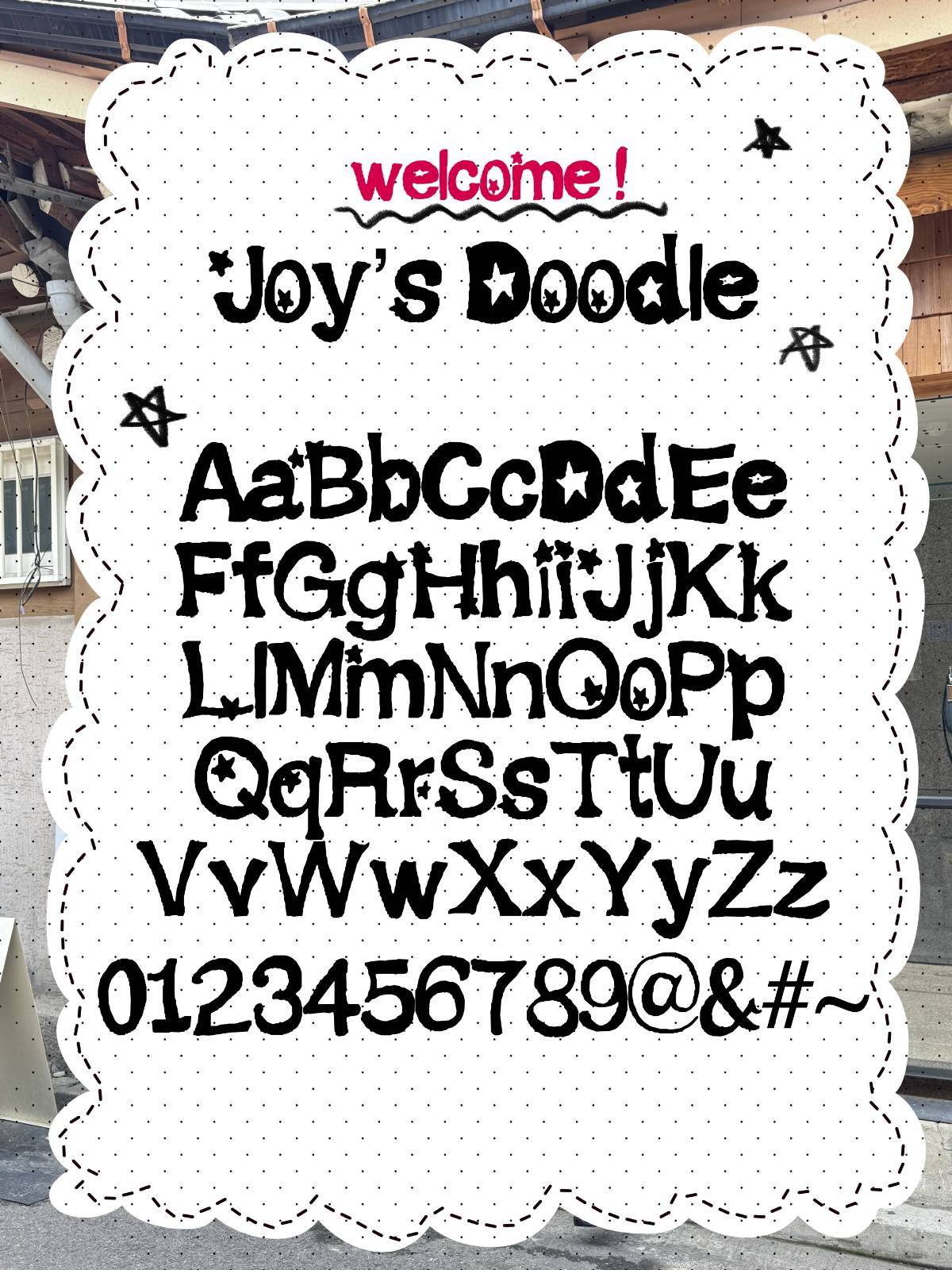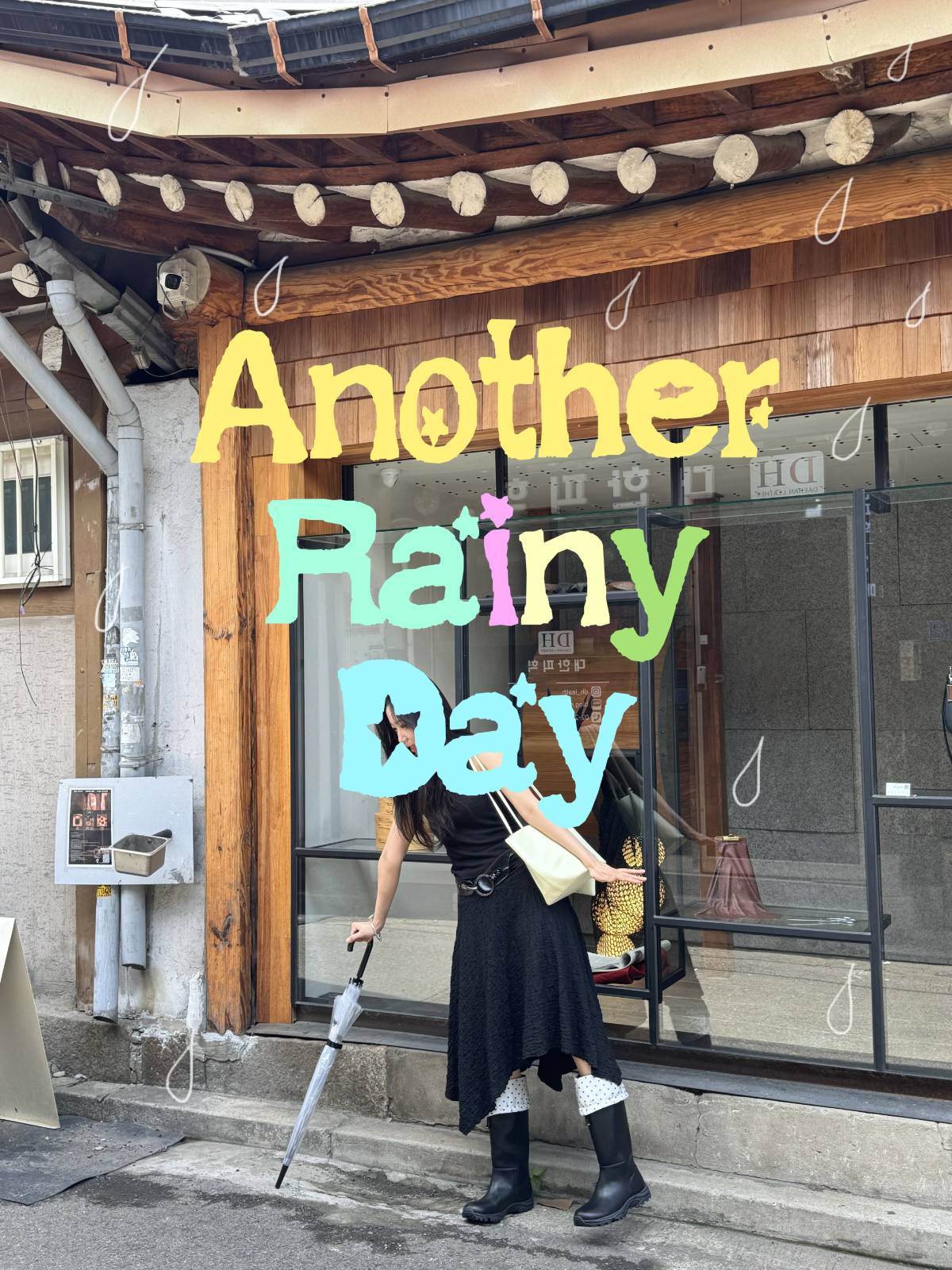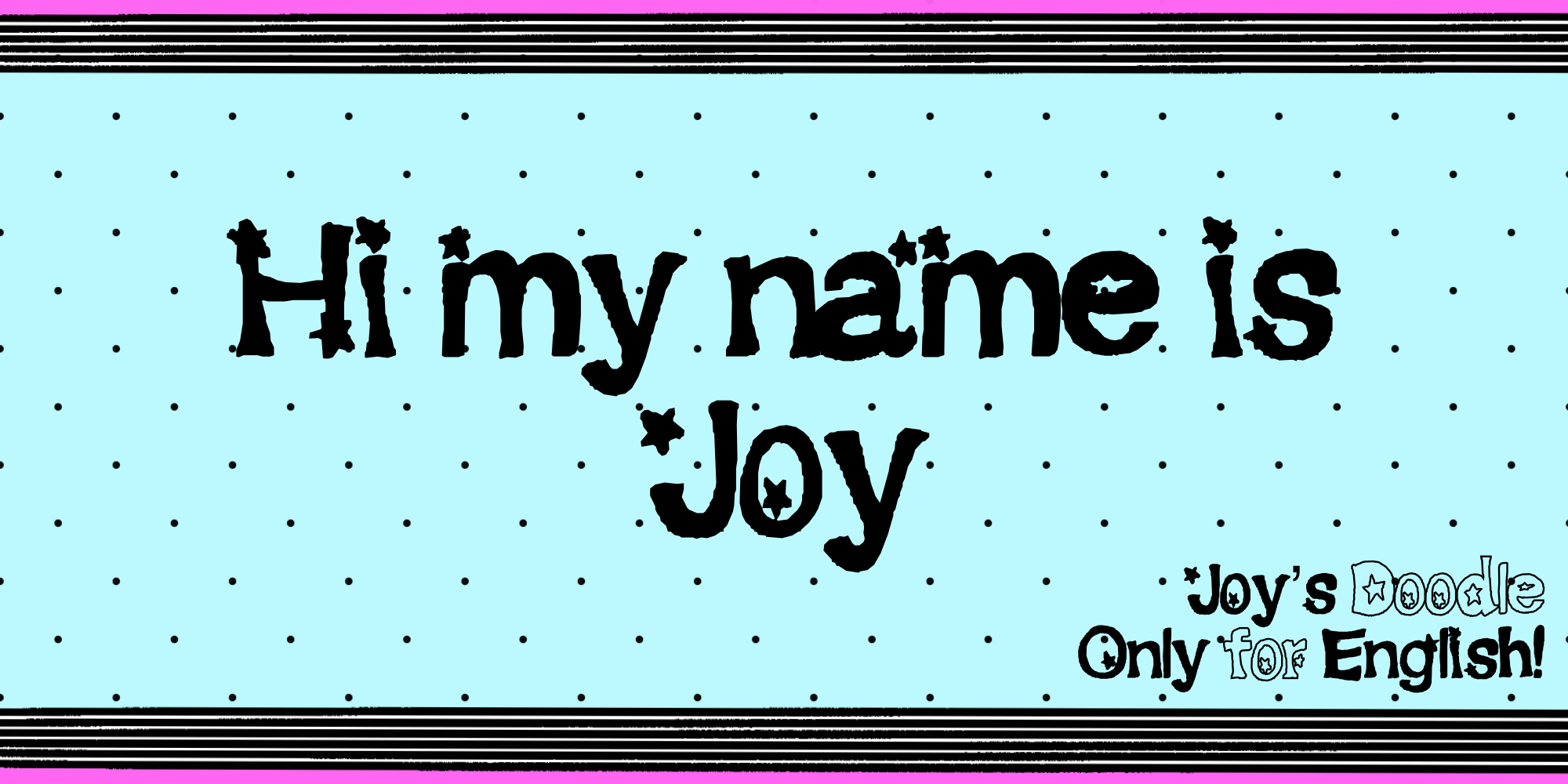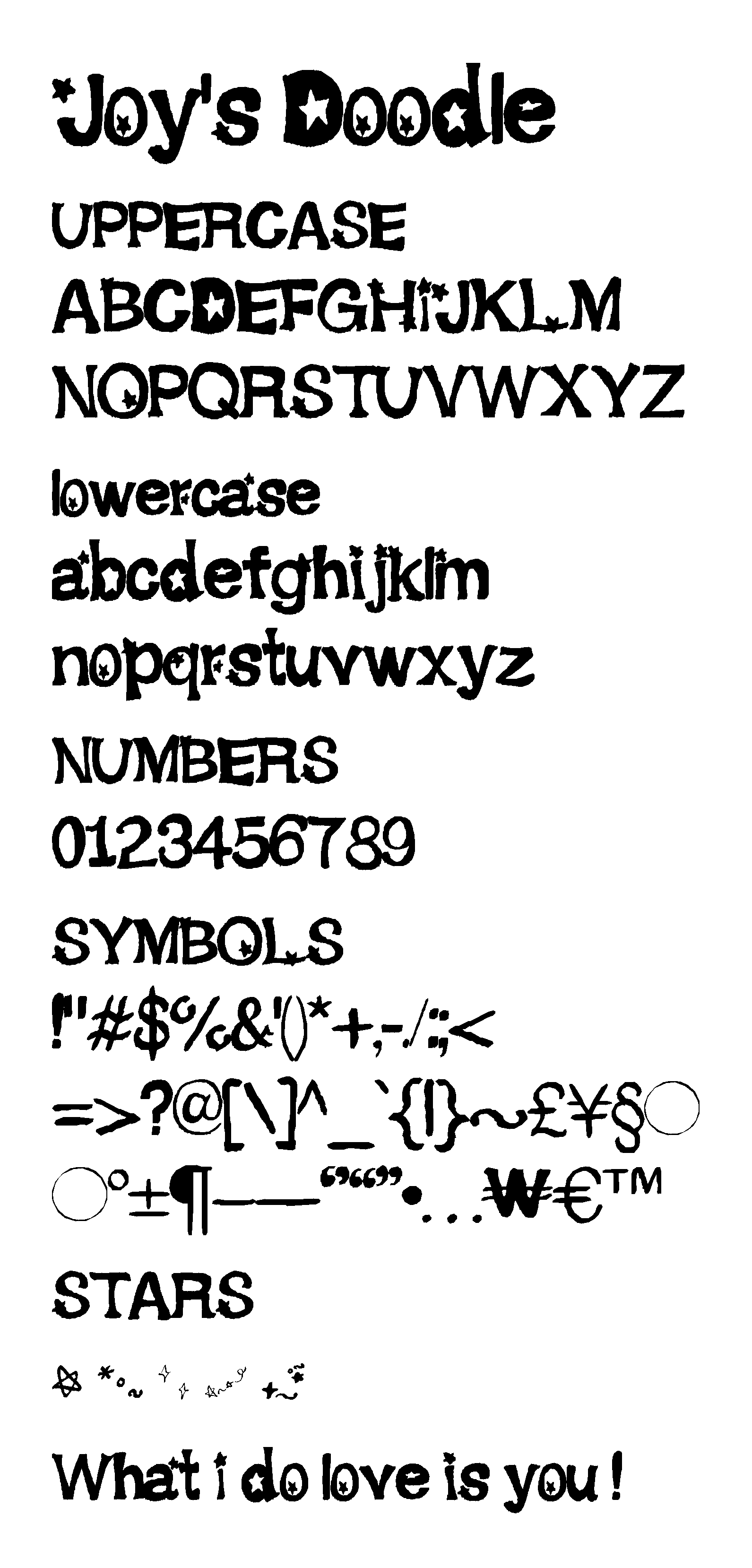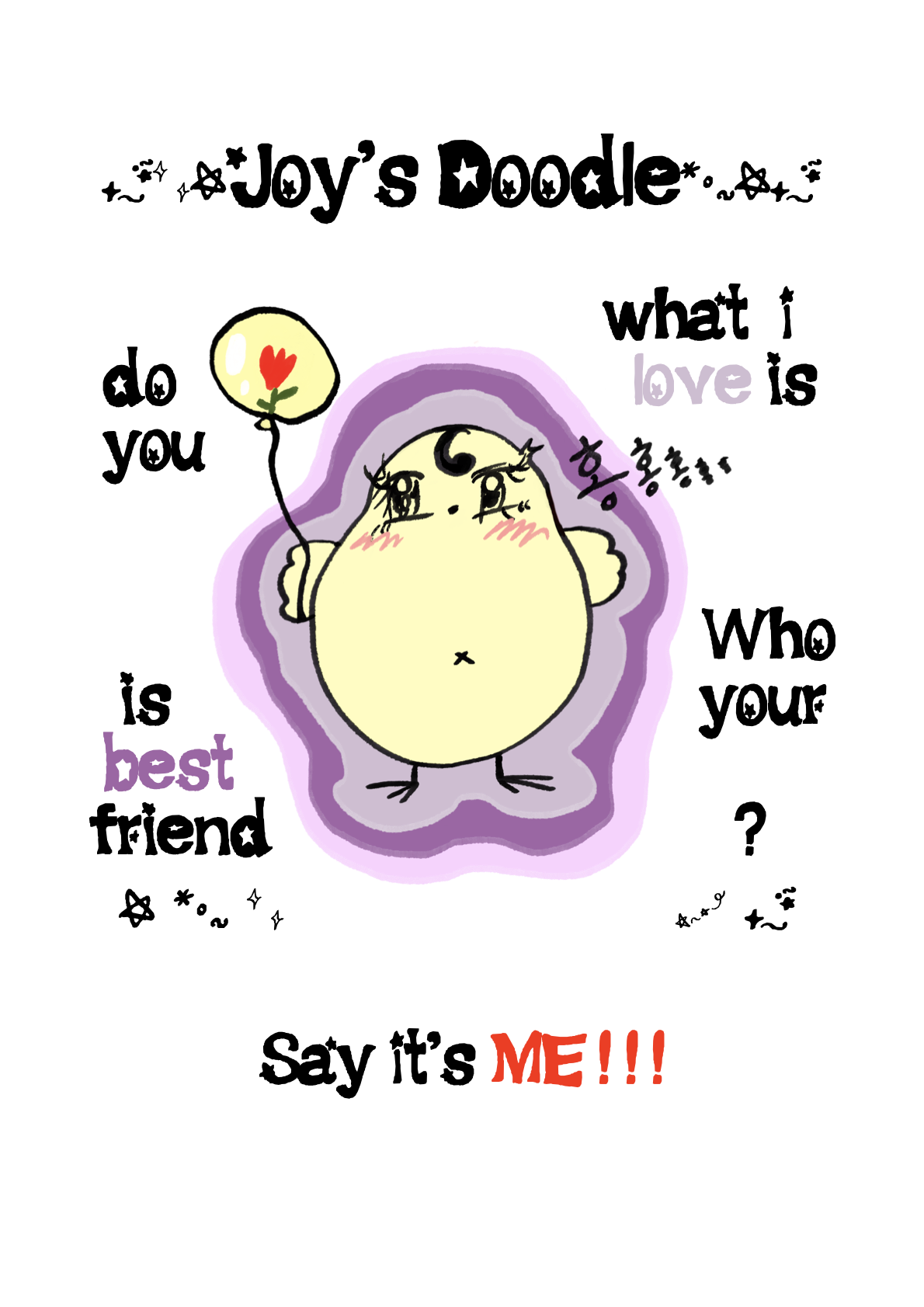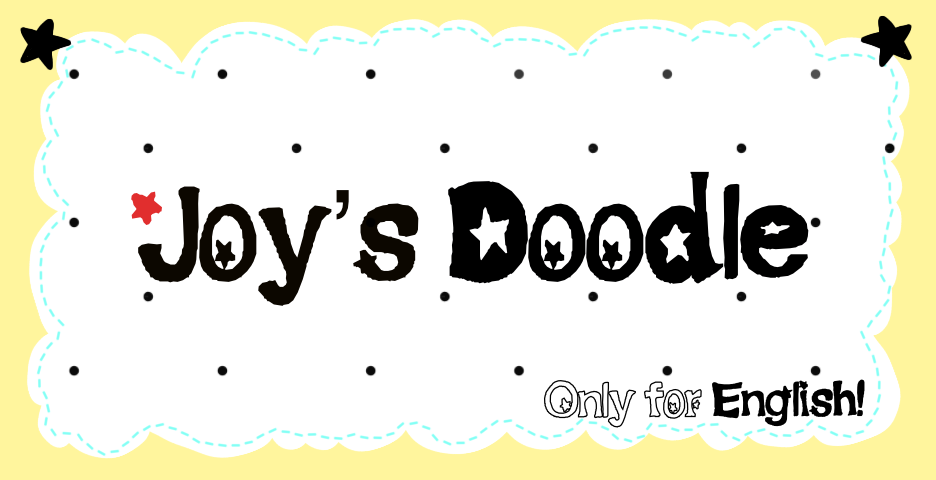
영상이나 사진 제목으로 추천해요 !
Joy's Doodle
제 낙서로 만든 삐뚤빼뚤 귀여운 손글씨 폰트입니다 !
자간을 아주 좁게 설계해서 단어가 살짝 뭉쳐 보이도록 만들었어요.
로고나 타이틀, 썸네일용으로 추천해요 !
영문 전용 폰트로, 한글은 지원하지 않습니다 !
✨ 별 모양 쓰는 법
별 5종 (★ ☆ ✦ ✧ ✩) 에 포인트가 될 별모양 그림을 넣었어요 !